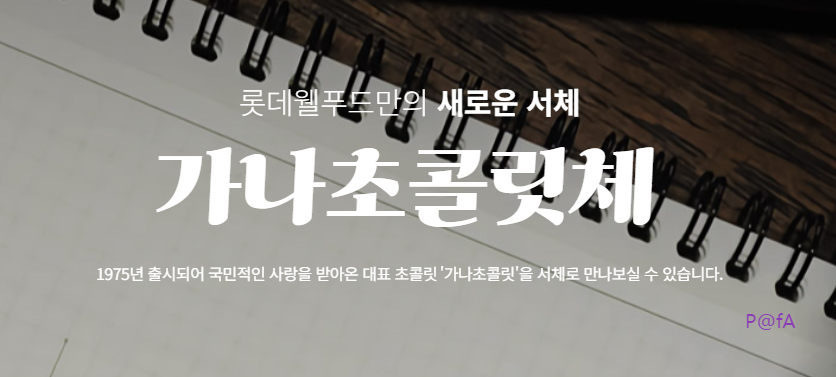
누구나 개인적인 용도뿐만 아니라 상업적인 용도 즉, 영리 또는 비영리 목적으로도 무료로 사용할 수 있도록 제공하는 무료 글꼴인 가나초콜릿체를 소개한다. 1975년에 출시되며 초콜릿을 대표하는 가나초콜릿을 서체로 구현한 해당 가나초콜릿체는 초콜릿의 부드러운 분위기와 풍미를 고스란히 폰트에 담고 있다. 다음에서 가나초콜릿체를 무료로 다운로드해서 컴퓨터에 설치하는 방법을 비롯해서 사용하는 자세한 방법을 확인할 수 있다.
상기 이미지에서 보듯이 글자의 기울기를 활용해서 초코릿을 부러뜨릴 때의 경쾌한 느낌과 곡선을 활용해서 초콜릿에서 전해지는 부드러운 맛을 표현하고 있다.
이렇듯 자소가 지닌 기울기와 유연한 곡선이 도드라진 특징인 가나초콜릿체는 단일 폰트로 제작되어 TTF 포맷과 OTF 포맷으로 각각 무료로 제공된다.
전반적으로 곡선을 적극적으로 활용하면서도 미세한 기울기 조정을 한 글꼴임을 확인할 수 있다.